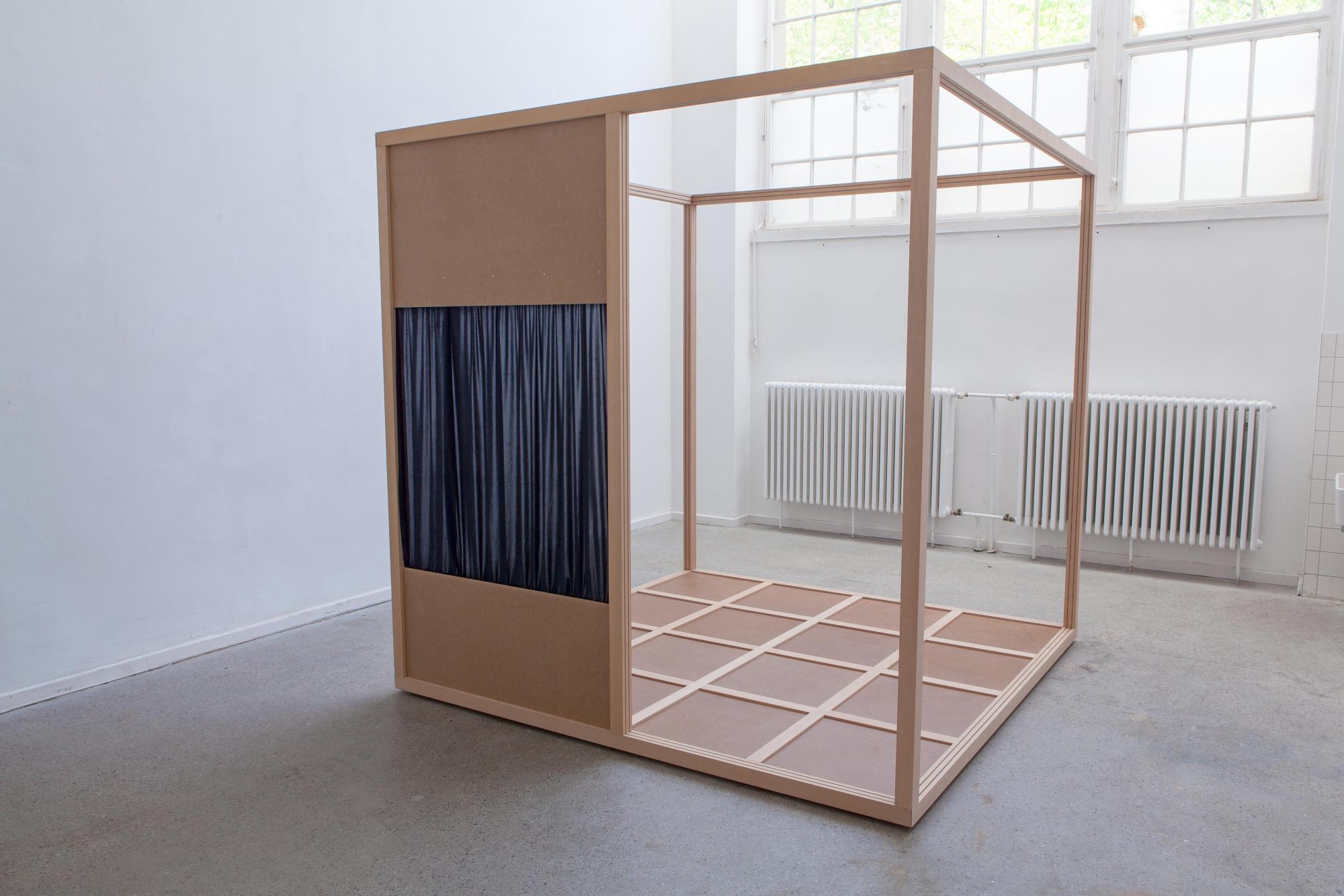
Welche Schrift für Portfolio?
Hallo. Ich gestalte ein Portfolio (pdf, nicht Druck...) mit Skulptur, Installation und ein bißchen Zeichnung für eine Bewerbung im Szenenbild. Nun bin ich auf der Suche nach einem passenden Font und kenne mich in der Sache nicht aus. Es wird nur kurze Textpassagen und relativ viel Weißraum um den Text herum geben.
Im Beispiel habe ich Aspen gewählt, das schaut mir aber noch nicht recht stimmig aus. Ich denke die Schrift sollte sich irgendwo zwischen den Polen minimalistisch/nüchtern und verspielt befinden, eine starke Schrift mit eigenem Spirit, die einen zeitgenössischen Look hat, fände ich super.
Bestenfalls würde sich der Font/die Fonts auch noch für Lebenslauf/Anschreiben eignen, muss aber nicht, und mich natürlich nicht arm machen:)
Könnt ihr was empfehlen? (Merci!)
Ich hänge was an Bildmaterial an, sonst würds wohl schwer.
… irgendwo zwischen den Polen minimalistisch/nüchtern und verspielt …
Mir kommt da was ganz Dünnes, Feines, Geometrisches wie die AB One in den Sinn, wo die Konstruktion mitschwingt
oder eine druckvolle Slab wie die
Aber das Feld zwischen minimalistisch/nüchtern und verspielt ist weit …
Hej, ich denke auch an geometrische Fonts. Und wenn Du die verspielte, zeitgemäße Komponente suchst, ist sowas hier gerade relativ angesagt:
Aber wie @bertel schon sagte: Bei dem Briefing geht noch sehr viel mehr, hier ein paar Beispiele für weniger geometrisch angelegte statische Fonts, ähnlich der von Dir gewählten Aspen, welche aber dennoch etwas geradliniger gestaltet sind:
Hallo @Norahanss!"§$, statt eines Alternativvorschlages von mir mal die Rückmeldung, dass ich die Aspen hier für treffend gewählt halte (das gibt es hier vermutlich selten genug).
Die Schrift harmoniert formal mit dem behandelten Thema und den bisher gezeigten Abbildungen und erfüllt für mich auch die von dir beschriebenen Kriterien.
Für Lebenslauf, Anschreiben und andere längere Texte eignet sie sich ebenfalls, weil sie für eine Groteske ihres Genres noch relativ ruhig läuft und als Fließtextschrift auch nicht zu sehr als »ungewöhnlich« ins Auge sticht.
Was genau stört dich an der Aspen, dass du eine andere Schrift wählen möchtest?
Ich finde die Aspen auch nicht schlecht, allenfalls etwas warum/rund für die Arbeiten, und nicht so gaanz gut als eigens Element vor viel Weißraum, ich glaube hier fahre ich doch etwas geradliniger noch besser.
@bertel@R::bert Ich versuch es also noch mal in genauer.
Ich korrigier mich etwas in Sachen zeitgemäß und verspielt; allzu jung und aktuell soll es gar nicht werden.  Das Portfolio bildet Arbeiten aus mehreren Jahren ab, da sollte die Schrift (die für Erklär Passagen gedacht ist, quasi wie im Museumskatalog), eine gewisse Ruhe und Zeitlosigkeit haben, nicht mit den Arbeiten konkurrieren oder als eigenes gestalterisches Element krass in den Vordergrund rücken, mehr "im Hintergrund" auf gute Art ihren Dienst tun.
Die Fractul und Neulis sind mir da zB schon zu hip und zeitgemäß, da suche ich nach einer Schrift, die sich etwas mehr "im Hintergrund hält", ohne charakterlos clean zu sein. DM Mono finde ich ganz cool, aber fürs Portfolio auch eher "too much". AB One, da finde ich die Leichte gut, aber die Schrift auch sehr aktuell.
Die Ambit gefällt mir schon ziemlich gut, die zieh ich in Betracht und teste sie gleich mal im Dokument!
Habt ihr noch ein paar Ideen?  Stück weit ruhiger, klassischer als die Beispiele, ruhig was "bewährtes", eher geradlinig als verspielt.
Habt ihr noch ein paar Ideen?
Na klar! :rockon:
Stück weit ruhiger, klassischer als die Beispiele, ruhig was "bewährtes", eher geradlinig als verspielt.
… könnte man jetzt alle als ruhigere, diszipliniertere Alternativen zur Aspen und Ambit bezeichnen. Allerdings habe ich erstmal nicht auf den Preis geschaut. Ich kann Dir aber sagen, dass man die Adelle (ohne ẞ), Ballinger oder Real über die Creative Cloud aktivieren und die IBM Plex darüber hinaus auch kostenlos lizenzieren kann.
ruhig was "bewährtes", eher geradlinig
Da fände ich die DIN nicht unpassend. Konkurriert nicht mit dem Inhalt.
Witzig. Die DIN kam mir bei dem Thema als erstes in den Sinn, allerdings passen die Attribute verspielt und zeitgenössisch aus dem Ursprungsthread nicht so wirklich. Bewährt und geradlinig allerdings schon :-D
:Schmunzel: Und ich wollte eigentlich noch mit Alternativen zur Impact (ehem. DIN) kommen, hab’s mir dann aber verkniffen um nicht zu viele Kandidaten ins Spiel zu bringen. :-|
Hallo Nora,
ich habe diesen Thread jetzt erst entdeckt, deswegen mein später Beitrag. Mein Tipp: Schau Dir doch auch noch die GT Walsheim an. Ich habe das Foto Deiner Arbeit weiter oben gesehen und spontan an diese Schrift denken müssen. Vielleicht gefällt sie Dir ja?